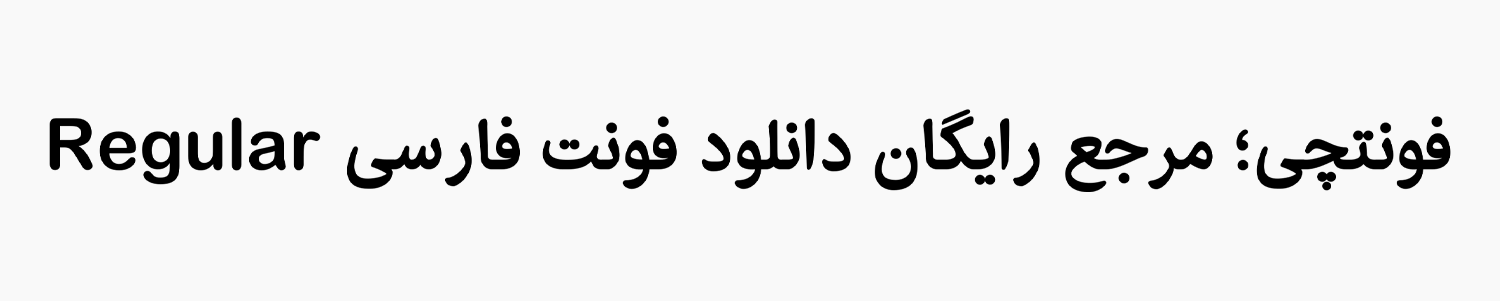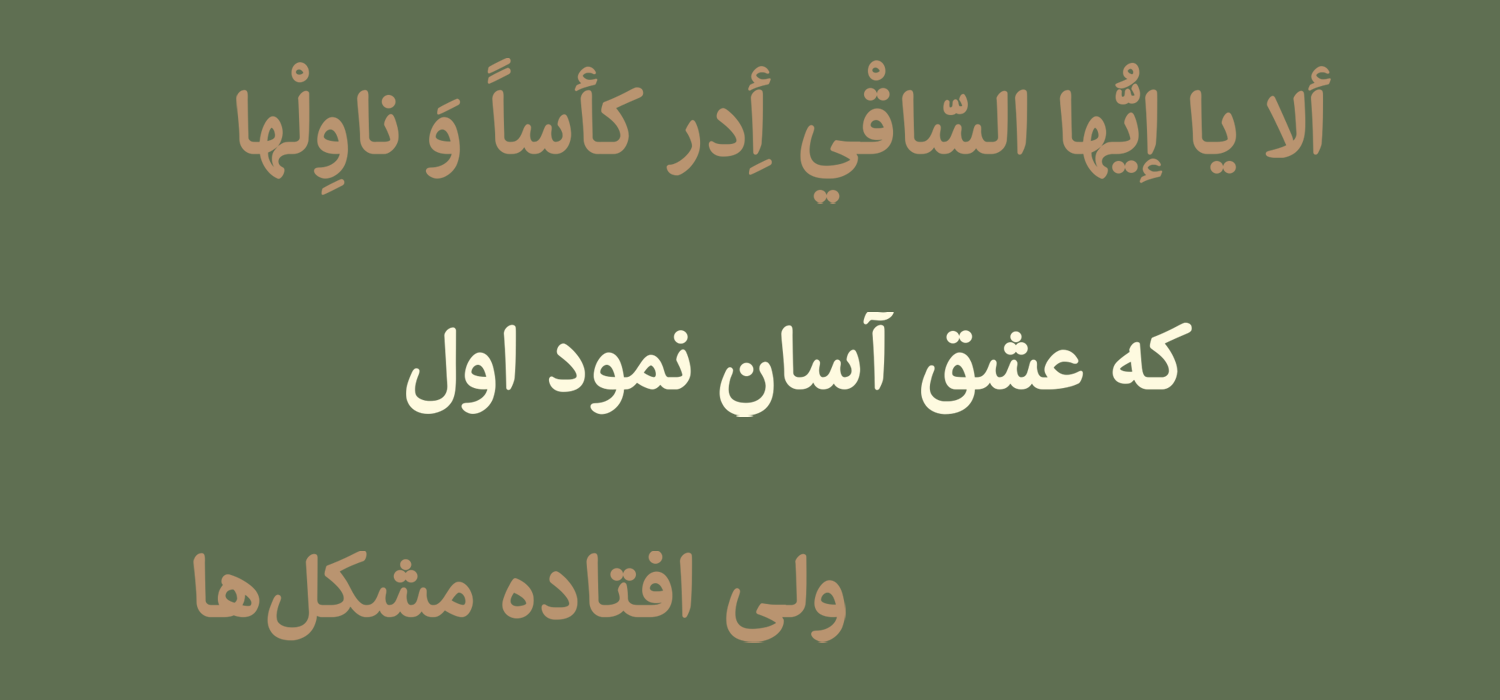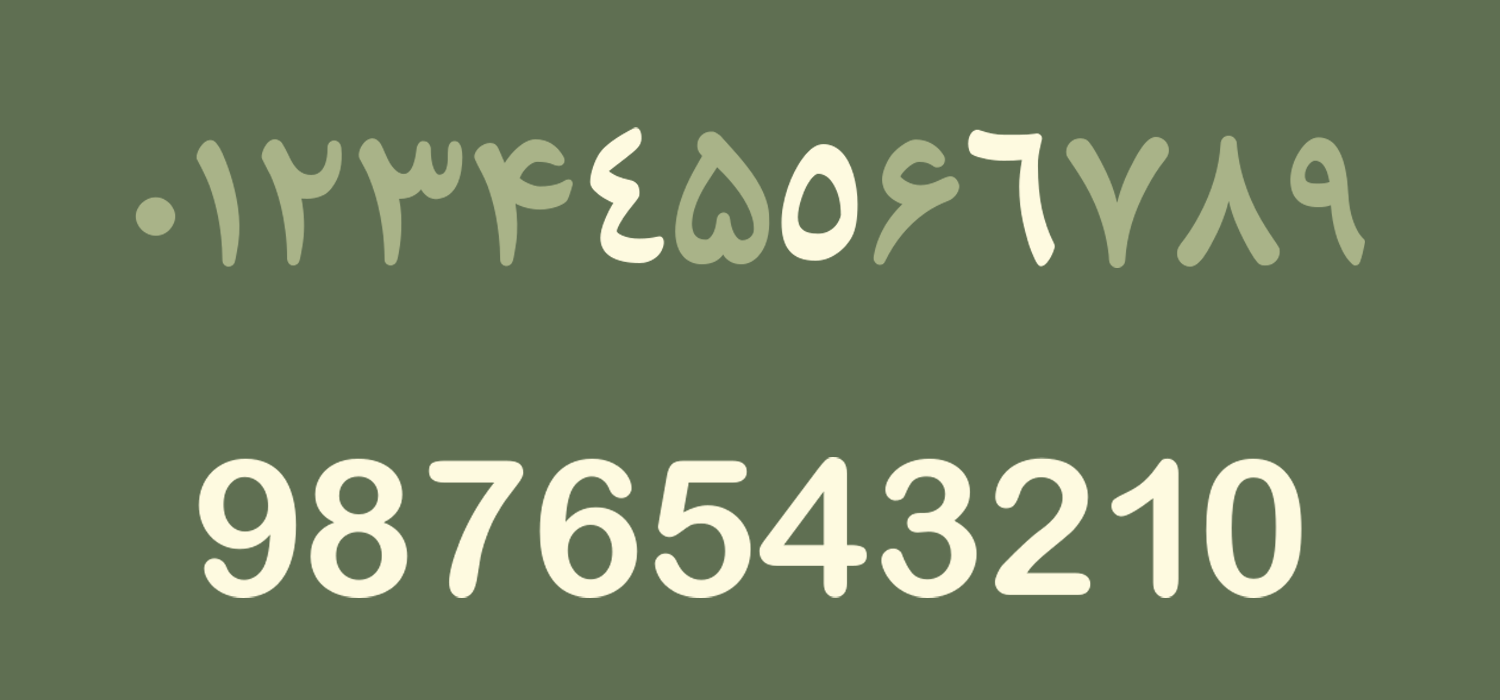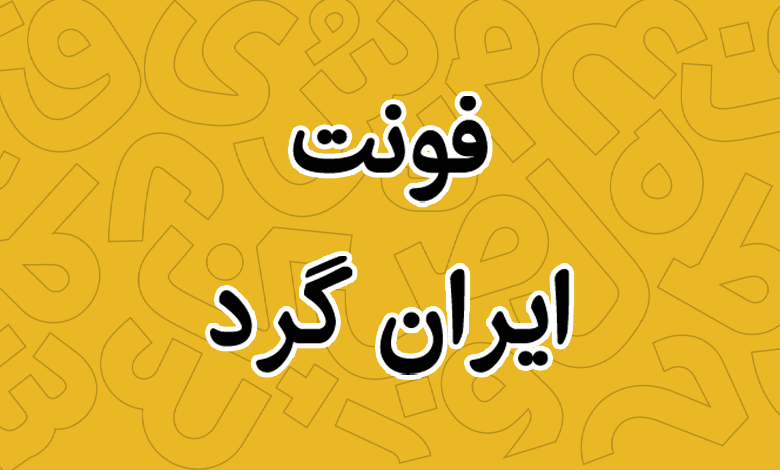
فونت ایران گرد (Iran Rounded)
فونت ایران گرد (به انگلیسی: Iran Rounded) فونتی رایگان است که بر اساس فونت خانواده ایران با سبک فانتزی ایجاد شده است. میتوان اینطور هم درنظر گرفت که این تایپفیس نسخهای بولد شده با لبههای مدور از فونت مذکور است که با هدف استفاده در کارهای نمایشی و فانتزی ایجاد شده است.
این قلم نیز مشابه برخی دیگر از فونت های رایگان فارسی، توسط زینب یدیسار در کارگاه طراحی فونت مسلم ابراهیمی ایجاد شده است. هدف این بوده تا هر دانشجو با ایدهای خاص یکی از فونتهای رایج آن سالها را دستخوش تغییراتی داده و یک تایپفیس از دل آن متولد شود.
در ادامه این نوشته از سایت فونتچی به نقد و بررسی قلم ایران گرد خواهیم پرداخت. فونتی که با کنار گذاشتن زوایای تیز و کمی بولدتر کردن خانواده فونت ایران، ساختاری نرم، نمایشی و صمیمی بهخود گرفته تا برای کارهای نمایشی خصوصا در حوزه چاپ کتاب کودک و نوجوان مورد استفاده قرار گیرد.
بررسی و دانلود فونت ایران گرد (Iran Rounded)
برای کارهای غیررسمی و نهچندان جدی استفاده از فونتهای فانتزی میتواند بهترین انتخاب باشد. فونت ایران گرد نیز جزو همین دسته قلمهای فارسی است که با ظاهر گرم و صمیمی خود، میتواند در کارهایی غیر رسمی همچون چاپ کتابهای مصور، چاپ مجلات، طراحی جلد یا انجام کارهای گرافیکی که نیاز است ارتباطی صمیمی با مخاطب برقرار شود مورد استفاده قرار گیرد.
این قلم تغییرات اساسی را به خود گرفته و به کلی دگرگون شده است که نتیجه آن ایجاد فونتی با خوانایی یکدست و بالا است که نسبت به فونت مادر خود، یعنی ایران؛ روحیه نرمتری دارد.
سبک طراحی و وزن فونت ایران گرد
در طراحی این قلم تمامی حروف یک ساختار بولد به خود گرفتهاند و اگر قرار باشد آن را با وزنهای متعددی که خانواده فونت ایران داشته است بررسی کنید، میتوان گفت که چیزی بین نسخه بولد و سیاه است.
جدایی از تغییر ضخامت، گوشههای تیز در تمامی قلم گرد شده تا ساختاری صمیمی و یکدست در قلم ایجاد کند. همین ویژگی این قلم را از یک سبک نسخ دورتر کرده است؛ تا حدی که دیگر نمیتوان گفت این تایپفیس اصلا فونت نسخ باشد.
پشتیبانی از ۵ زبان متنوع
فونت ایران گرد همچون مادر خود، یک فونت کامل است که از زبانهای متعددی پشتیبانی میکند. به لطف رسم خط فارسی مورد استفاده در سایر زبانهای عربی، کردی و اردو میتوانید با این فونت تمامی کاراکترها و گلیفهایی که در این زبانها وجود دارد را بر اساس استاندارد خود تایپ کنید.
صفحه کلید شما روی هر زبانی که قرار داشته باشد، حروف و کاراکترهای مختص به همان زبان تایپ خواهند شد. مثلا حروف «ک، ی، ه، ؤ، ئ» در زبان عربی یا حروف «ﮧ، ﮩ، ے» در زبان اردو با ساختاری کاملا متفاوت نسبت به حروف فارسی، دارای گلیف خاص خود هستند.
جدایی از حروف و کاراکترهای اصلی، این هماهنگی در بخش اعراب نیز بهچشم میخورد. تمامی اعراب فارسی و عربی ضمن قرارگیری در مکان درست؛ دارای همنشینی استانداردی با سایر کاراکترهای «همزه، تشدید، سکون» هستند که موجب تناسب کلمات شده و برخلاف فونتهای بسیار قدیمی اینطور نیست که موجب ایجاد بی نظمی یا چسبیدن به حروف مجاور شود.
این قلم از زبان انگلیسی هم پشتیبانی میکند. همان ایده گرد و بولد کردن حروف بر روی کاراکترهای لاتین نیز اعمال شده است. با این تفاوت که این تغییرات بر روی فونت اپن سورس Arial Rounded اعمال شده است.
دارای اعداد فارسی و عربی استاندارد
در این فونت کلیه اعداد فارسی و عربی دارای استاندارد خود هستند. زبان صفحه کلید شما روی هر زبان خاورمیانهای یا لاتین که باشد حروف متناسب با همان زبان تایپ میشود.
مشابه تصویر بالا که میبینید اعداد «۴۵۶» عربی در مقایسه با «۴۵۶» فارسی دارای ظاهر متفاوتی هستند.
مناسب تبلیغات و مطبوعات
با اینکه خانواده فونت ایران مناسب مطبوعات بوده و میتواند با کارکردی رسمی مورد استفاده قرار گیرد؛ اما تایپفیس ایران گرد که برگرفته از همین قلم است اینطور نیست. این قلم میتواند برای کارهای غیر رسمی و دوستانه مورد استفاده قرار گیرد.
اما به این معنی نیست که نتوان در صنعت چاپ، تبلیغات یا مطبوعات از این قلم استفاده کرد. برعکس؛ این فونت با ساختار نمایشی که دارد و بهویژه در اندازههای بزرگ خود را بهتر نشان میدهد میتواند برای کارهایی که جنبه ایجاد فضایی دوستانه دارند مورد استفاده قرار گیرد.
مثلا در حوزه تبلیغات بر روی بیلبوردها یا در حوزه چاپ کودک و نوجوان، این قلم فضایی صمیمی را ایجاد میکند که موجب جذب نگاه مخاطب خواهد شد. میتوانید با نصب این فونت در انواع نرمافزار گرافیکی همچون اینشات نیز بهسادگی با استفاده از گوشی به طراحی تصاویر بپردازید.
از آنجا که این فونت جنبه فانتزی و تزئینی دارد توصیه میکنیم از آن برای فونت متنهای کوتاه در سایت استفاده کنید. مثلا در بخشهایی همچون عنوان مطالب، تیترها، نقل قول و کادرهای رنگی که ضمن درشت بودن فونت در چنین بخشهایی موجب زیبایی سایت، بهبود خوانایی و کمک به کاربر در جهت یافتن بهتر بخش مورد نظر در محتوا خواهد شد.
این فونت با استفاده ترکیبی در کنار سایر فونتهای مناسب متن نظیر فونت وزیر میتواند خروجی مناسبی داشته باشد.
آخرین نسخه فونت ایران گرد ۱.۱ است که چند سالی از انتشار آن میگذرد. این فونت را میتوانید در یک وزن معمولی Regular اما با ساختار ضخیمی که دارد، برای کارهای نمایشی از آن استفاده کنید. خصوصا در عناوین که این قلم با سایز بزرگتر خود را بیشتر نشان خواهد داد.